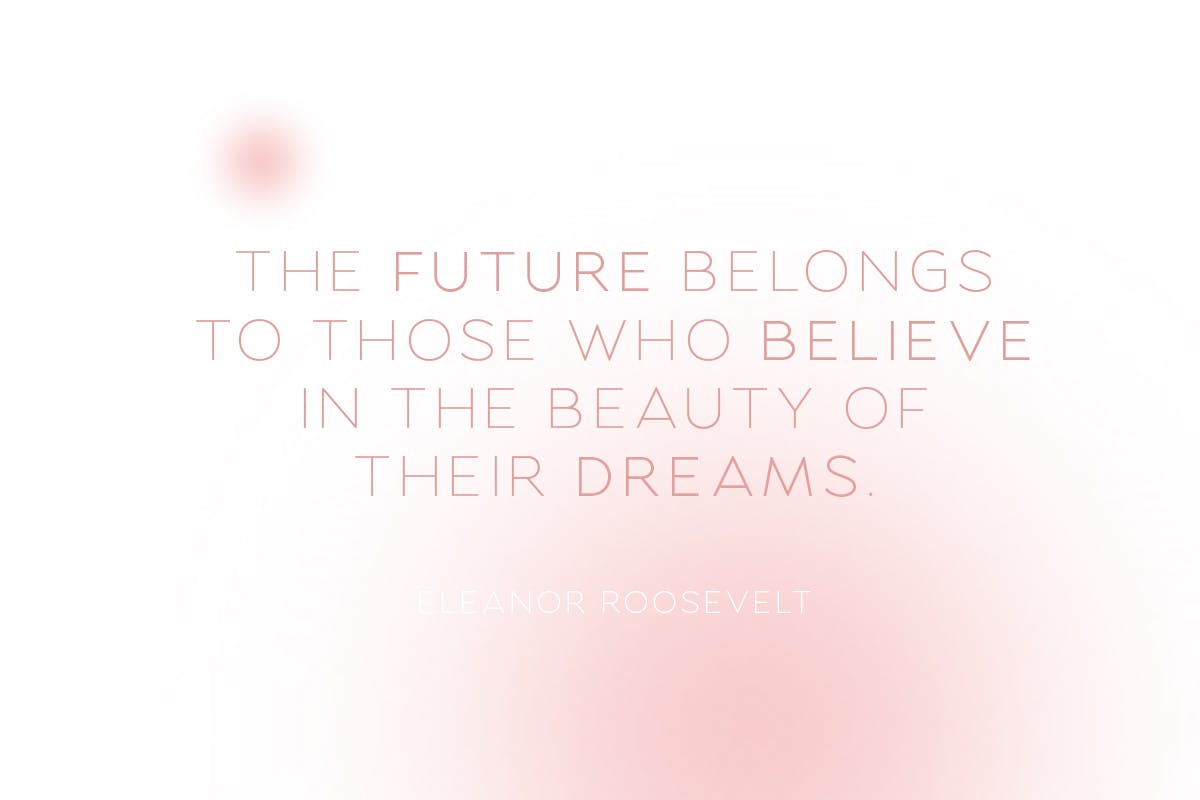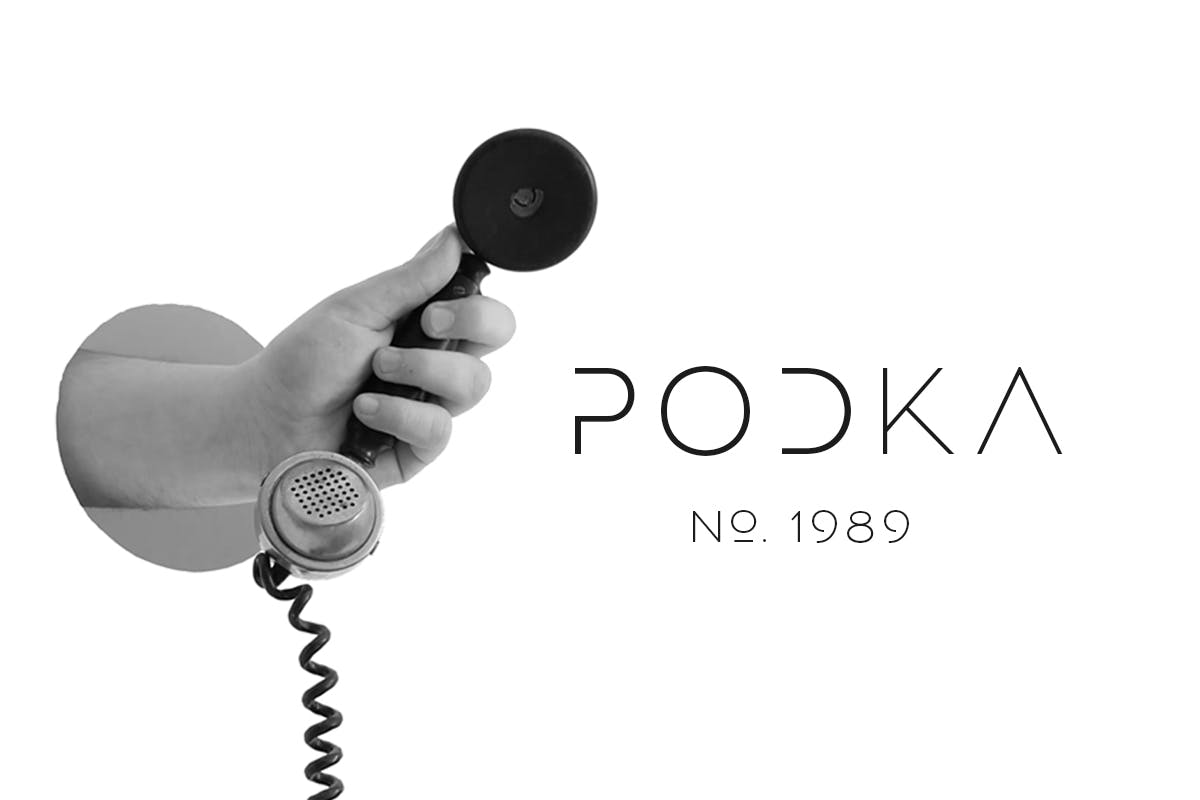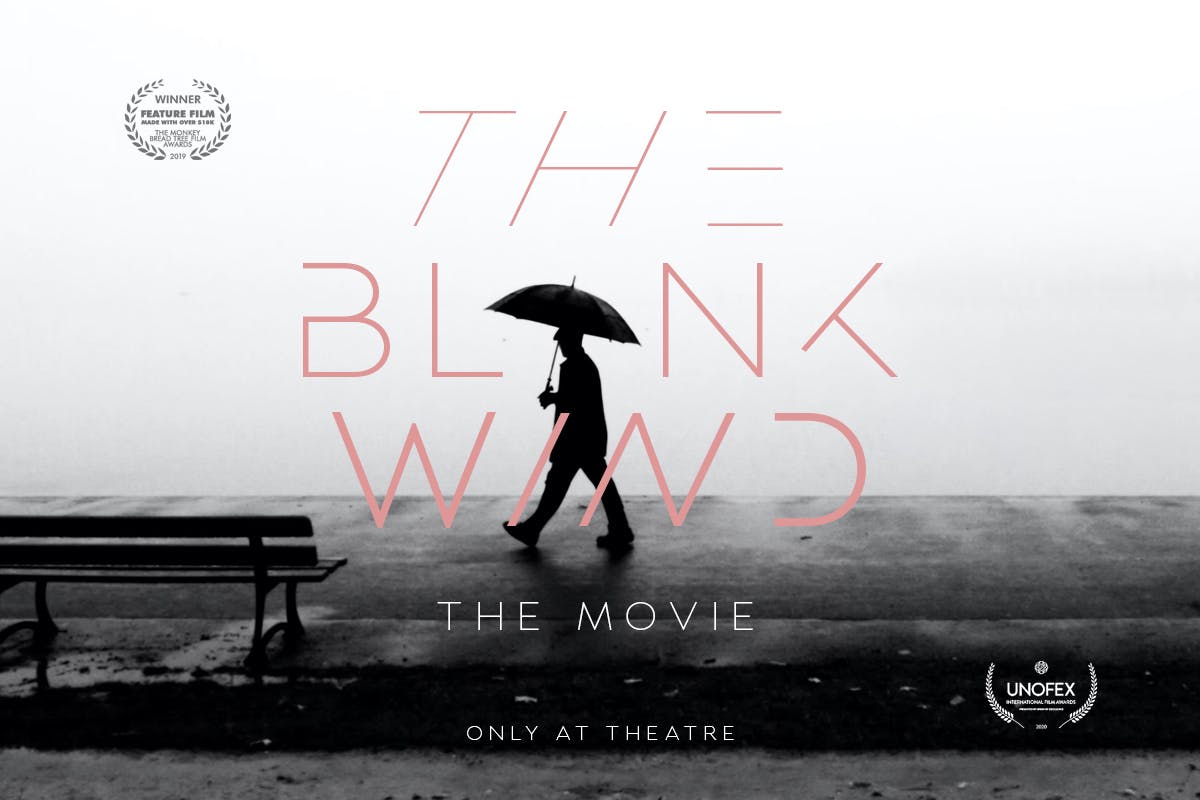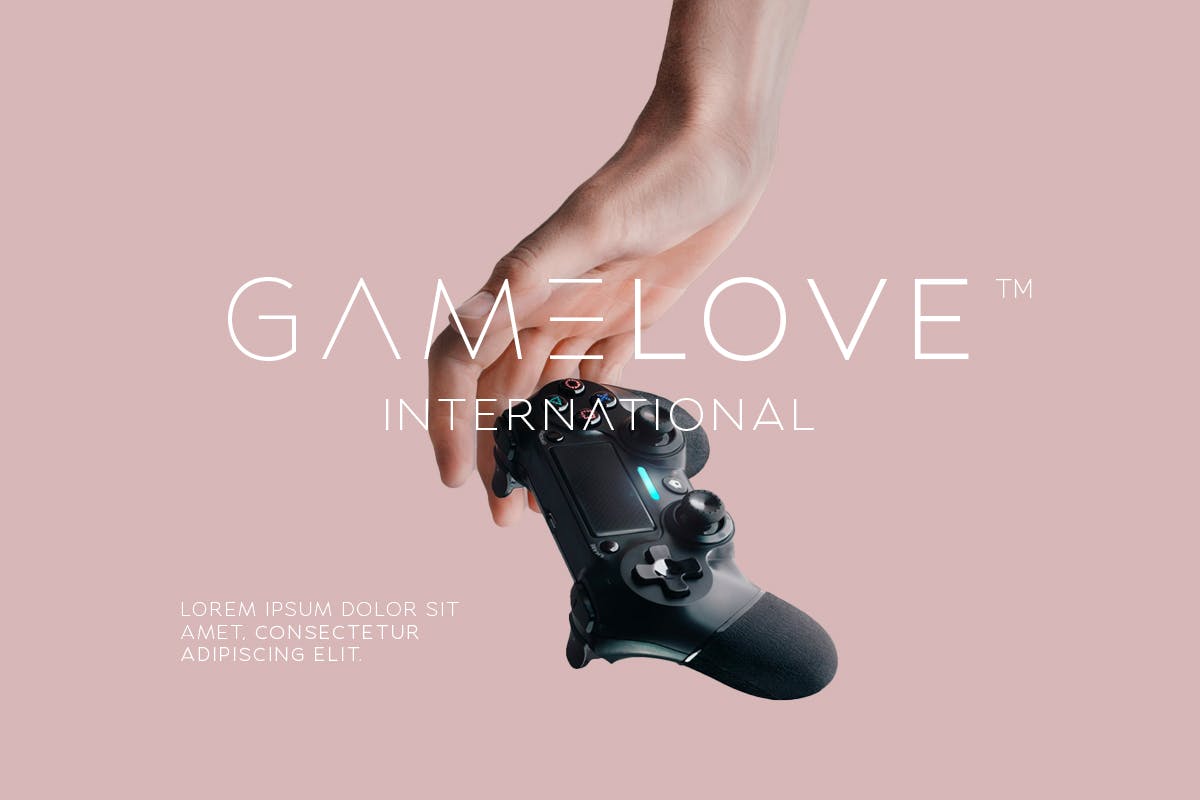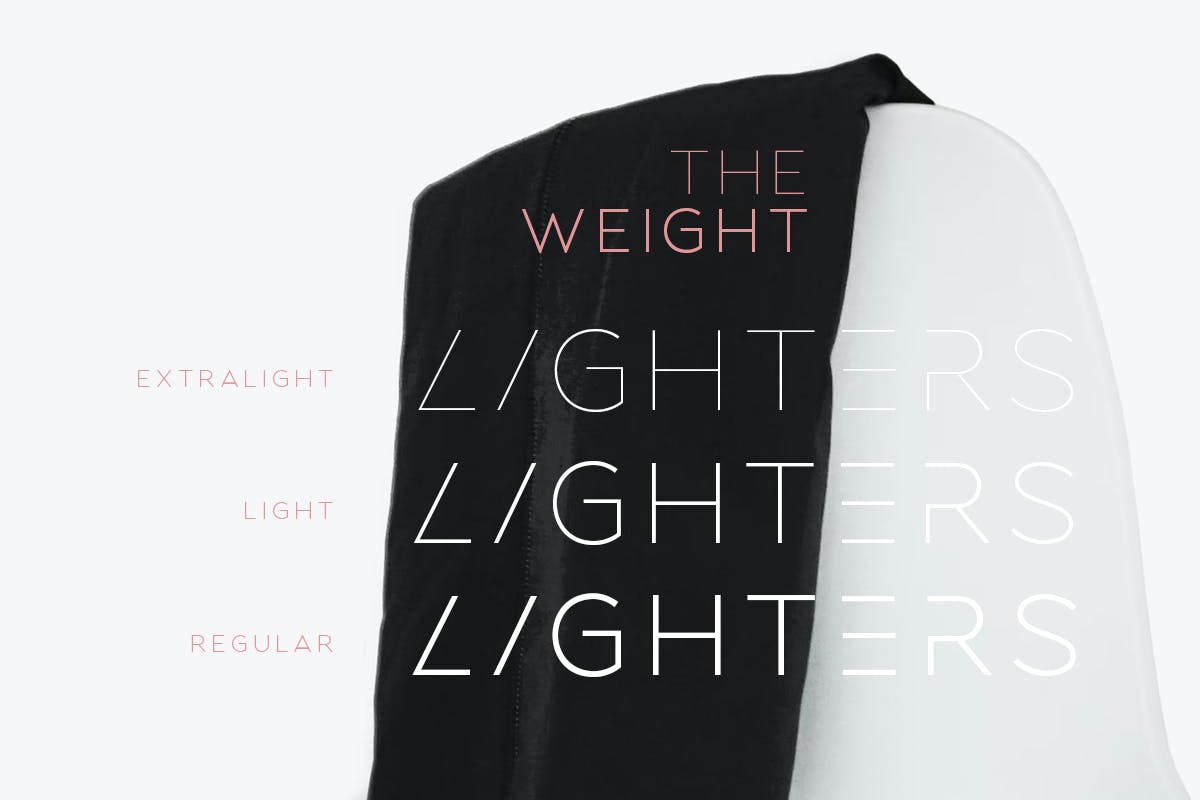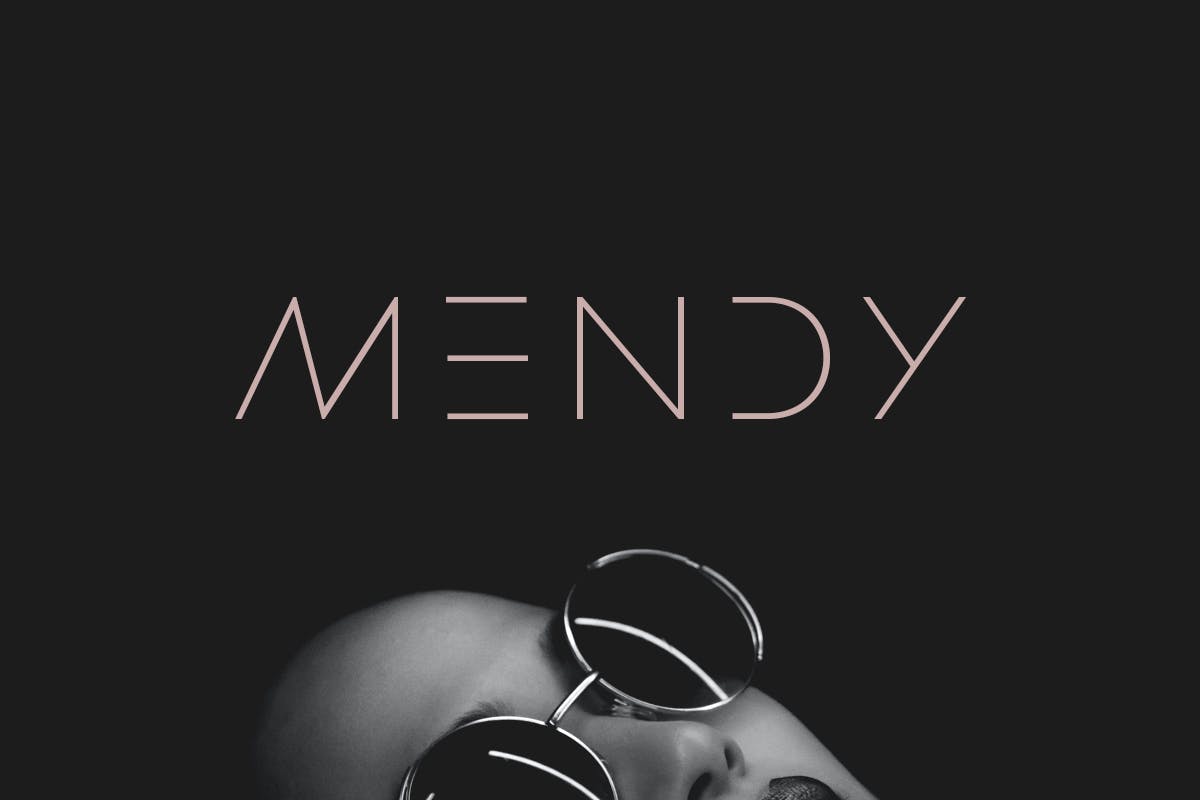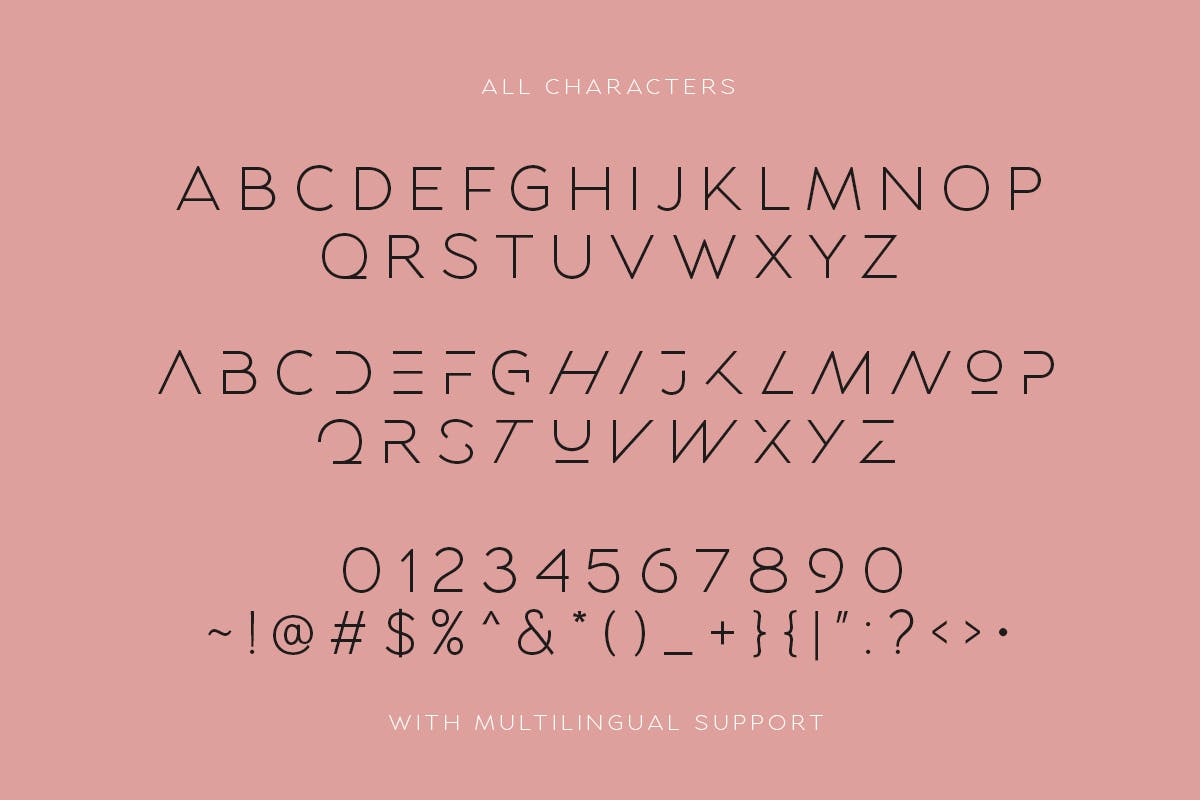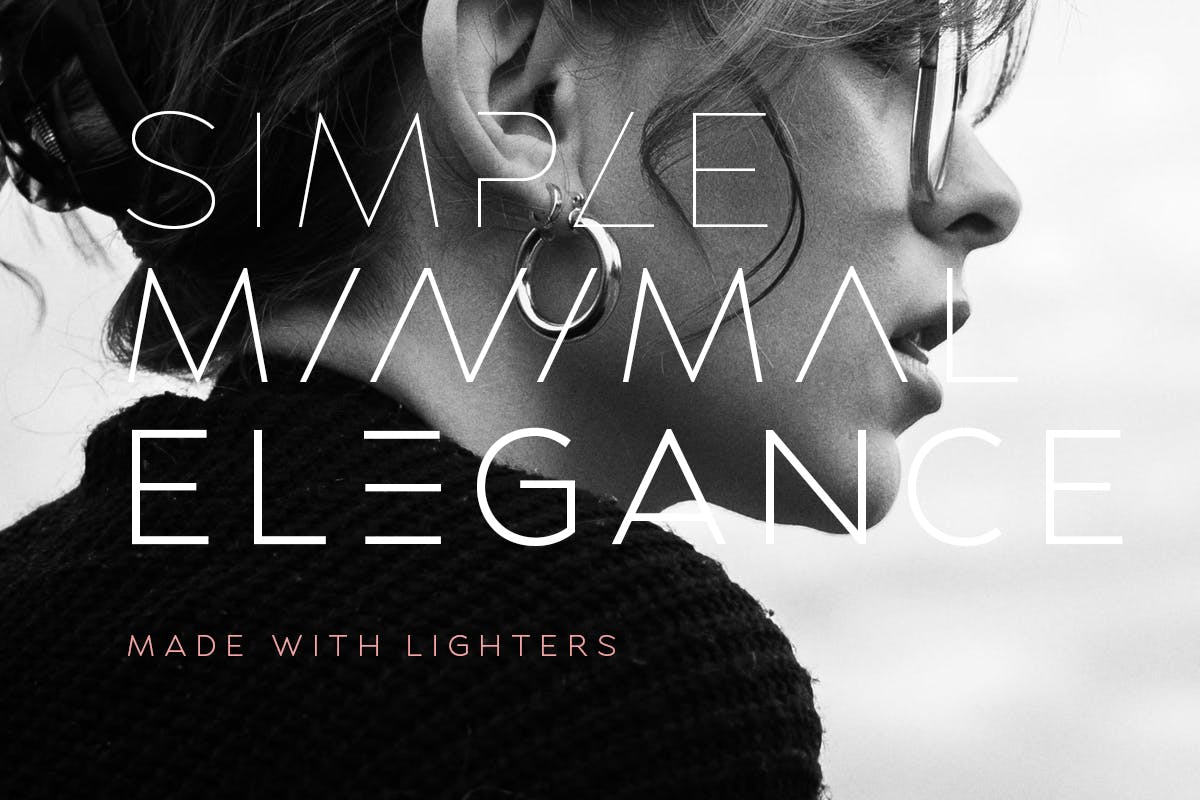
Lighters یک خانواده فونت لوگو سبک و مینیمالیستی است که با حروف کوچک منحصر به فرد خود، زیبایی و سادگی را به طراحی شما اضافه میکند. با سه سبک وزنی که میتوانید بهطور همزمان استفاده کنید، طراحی شما جذابتر خواهد شد. این فونت برای هر هدفی مناسب است، بهویژه برای طراحی لوگو و پوستر. شما میتوانید حروف بزرگ و کوچک را با هم ترکیب کنید تا لوگوی خود را بهروزتر کنید. این فونت همچنین شامل نمادها، اعداد و پشتیبانی چند زبانه است!